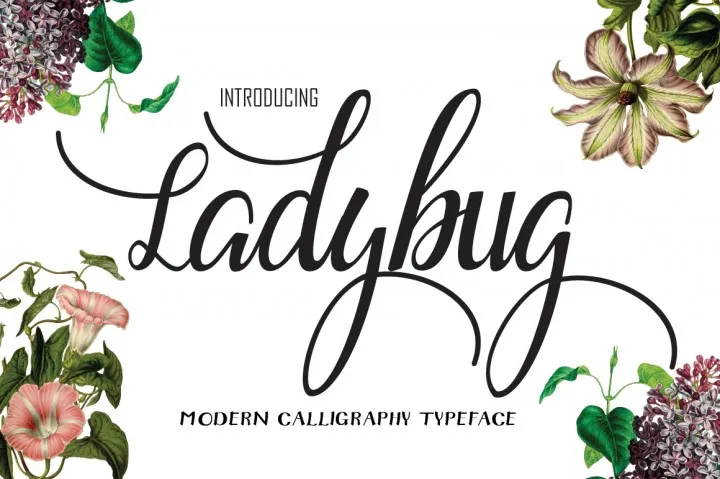
Ladybug Script Font – Download Grátis
Ladybug Script é uma elegante tipografia script premium que agora está disponível gratuitamente por apenas 7 dias no site TheHungryJpeg. Essa fonte foi criada pelo designer 178-MC e traz um ar refinado e sofisticado para qualquer projeto de design gráfico ou publicidade digital. Ideal para criar mensagens memoráveis em cartazes, sites ou materiais promocionais, Ladybug Script oferece uma linguagem única que se destaca. Seja você designer gráfico ou artista digital, essa fonte atende a todas as suas necessidades de design com sua escrita fluida e delicada. Aproveite este tempo limitado para baixar sua própria versão do Ladybug Script para uso pessoal. Não é necessário se inscrever ou gastar dinheiro adicional para usar esta incrível fonte que combina arquitetura moderna com um charme retrô elegante, tornando-a perfeita para qualquer projeto de design em que você esteja trabalhando.